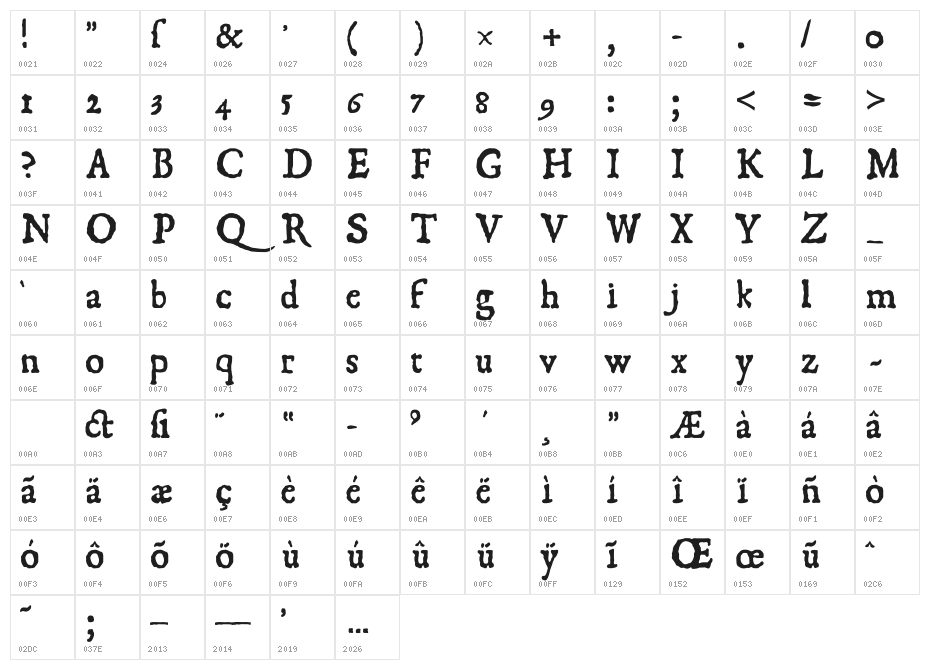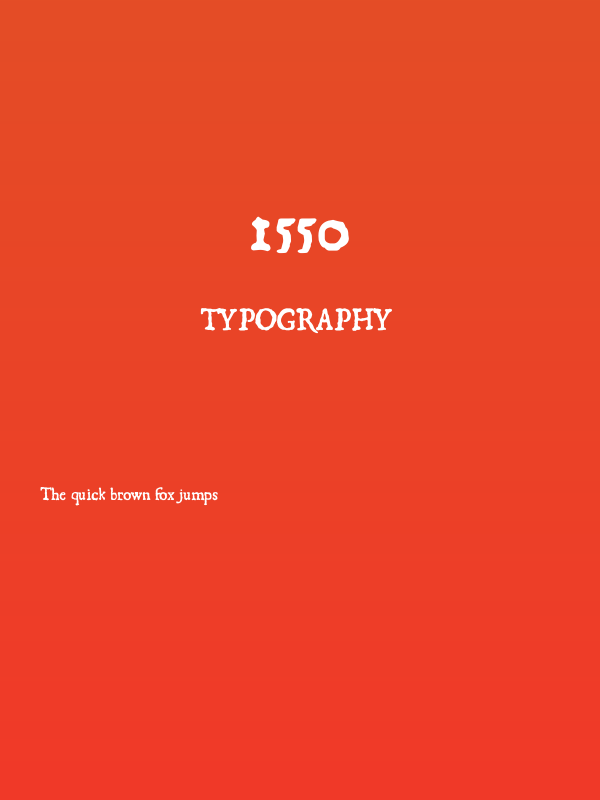
1550 Font
✎ Distorted Eroded
| Gesamtstil | Vintage |
| Anwendungsfall | Logos, Headlines, Posters |
| Vorgeschlagene Projekte | Perfect for vintage-themed posters, artisanal product packaging, rustic wedding invitations, and creative branding projects. |